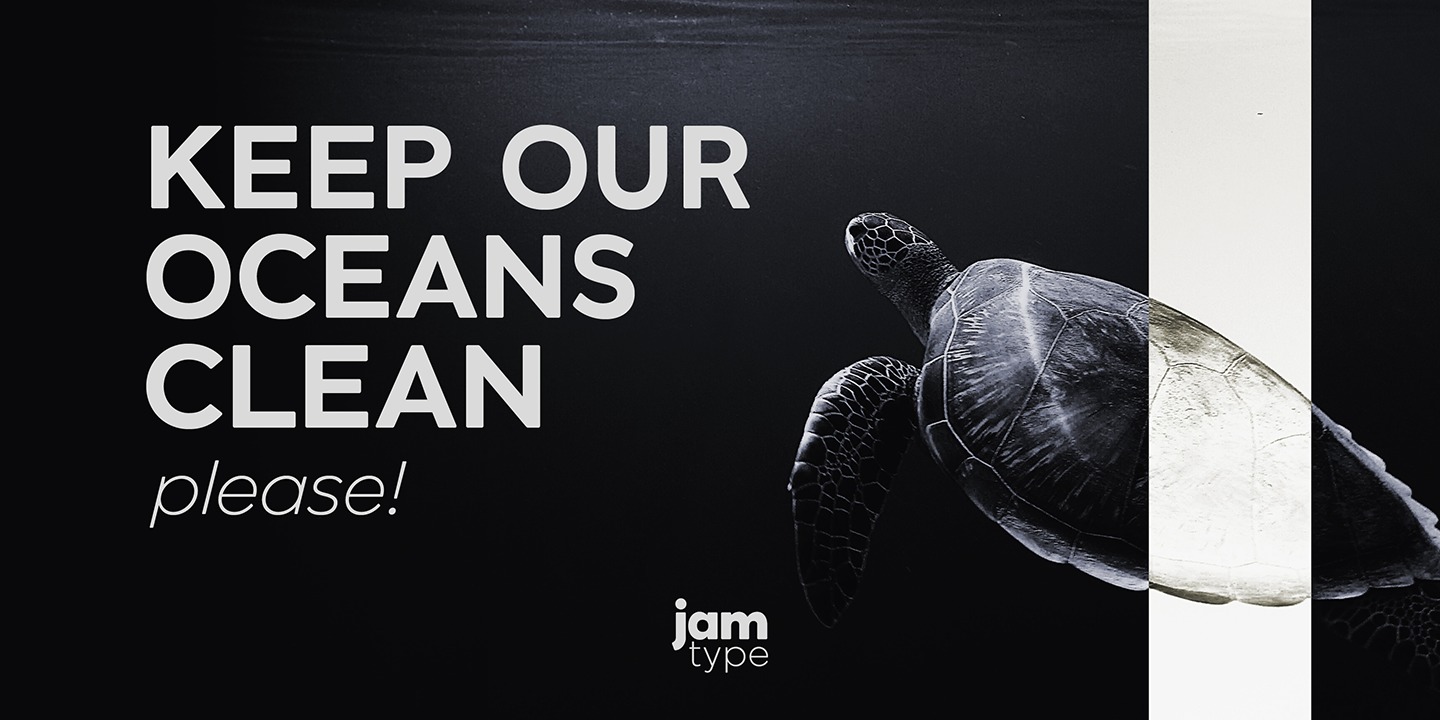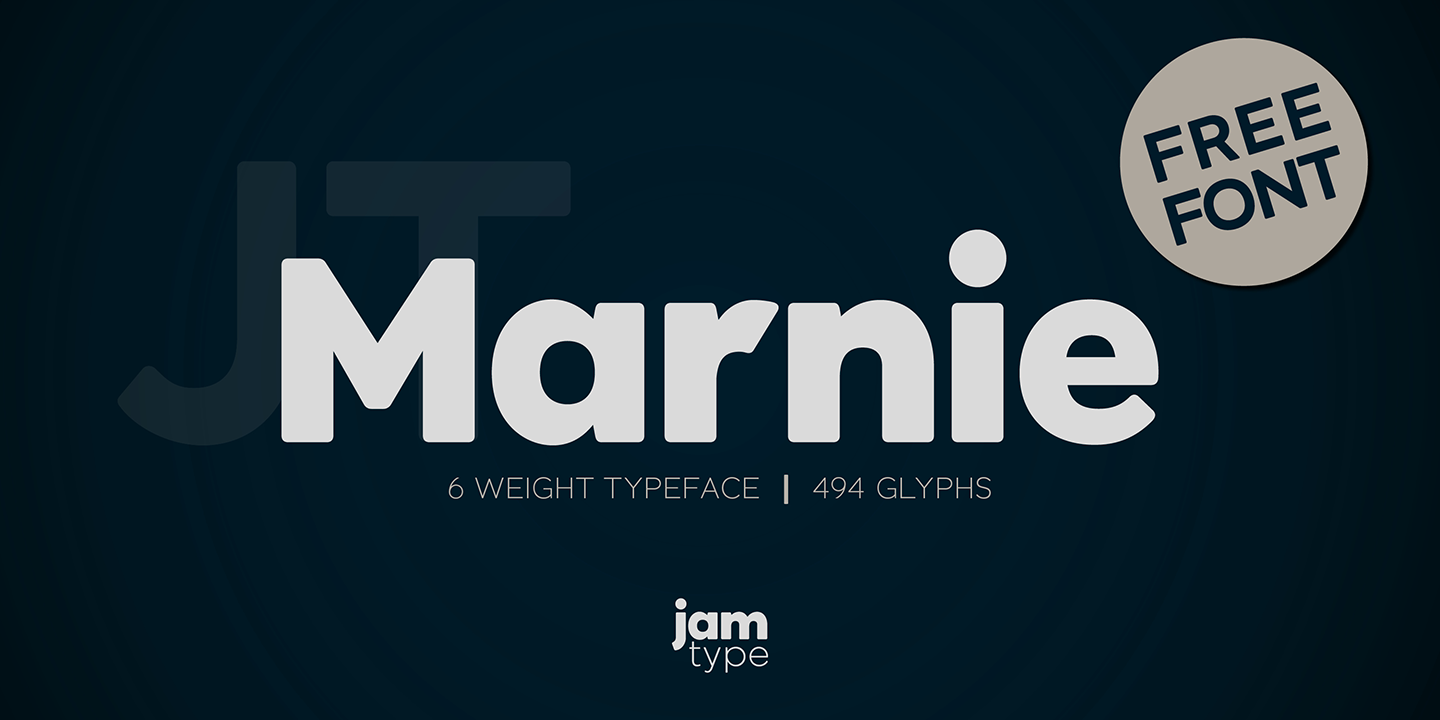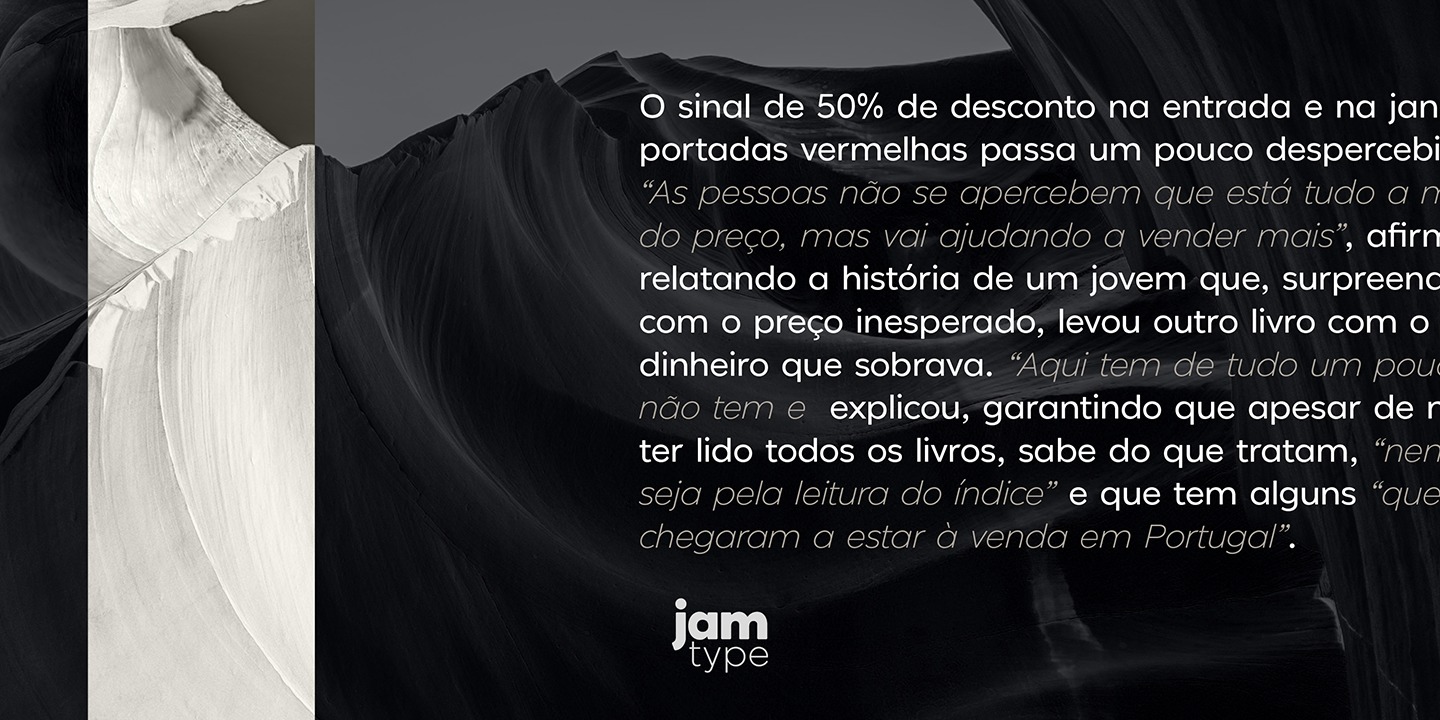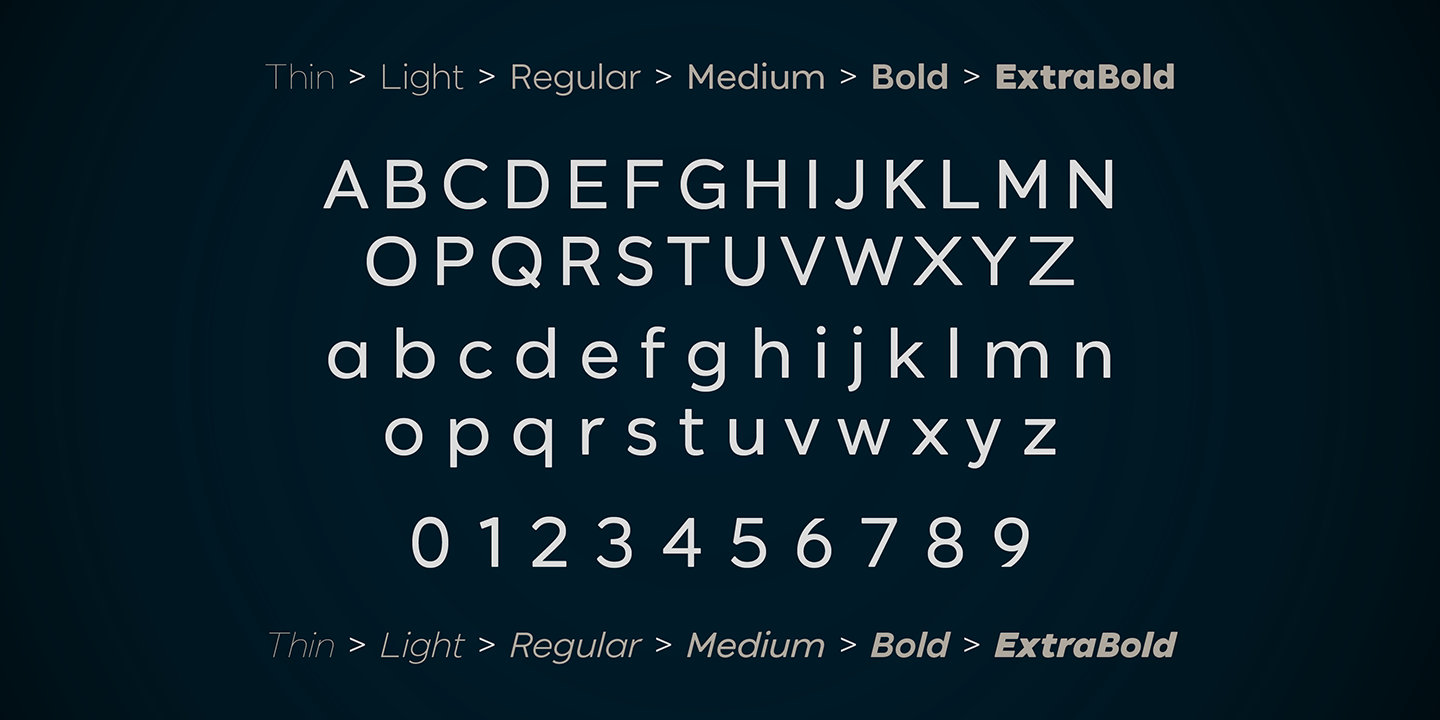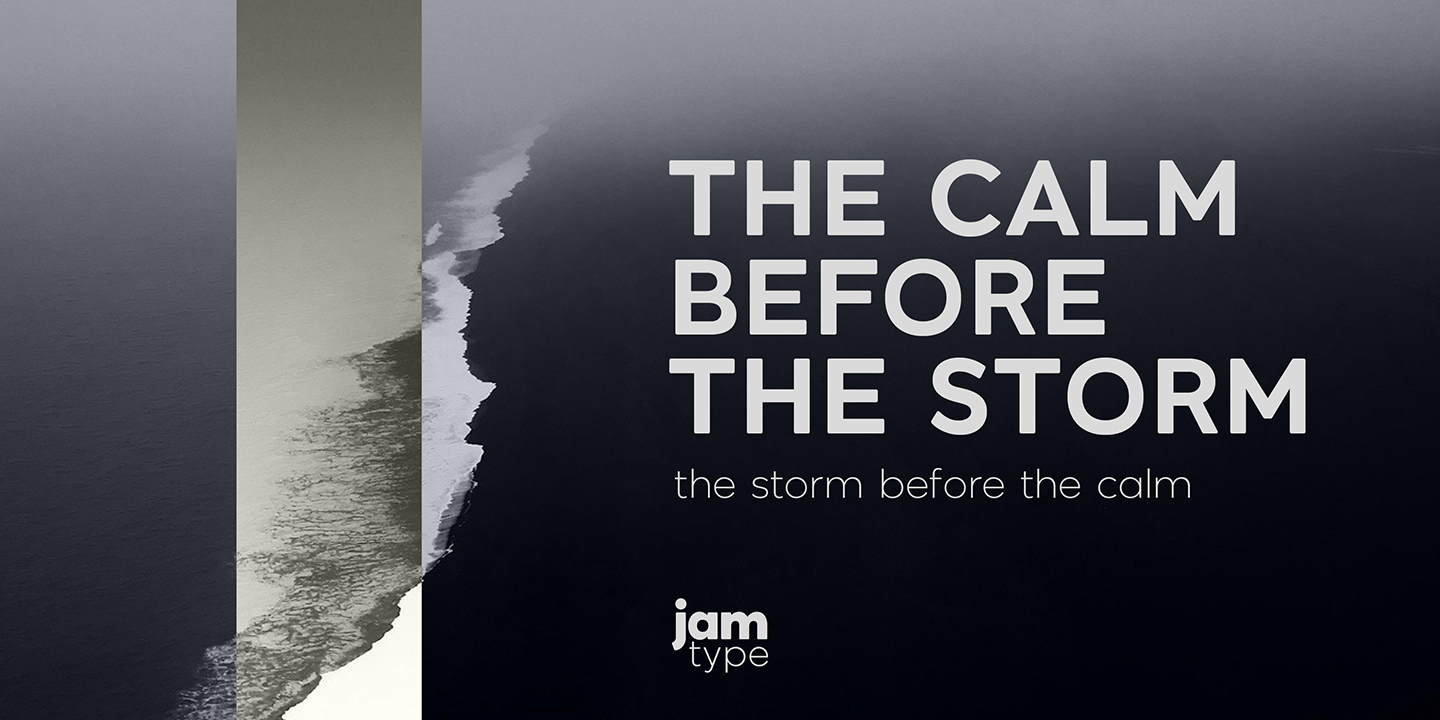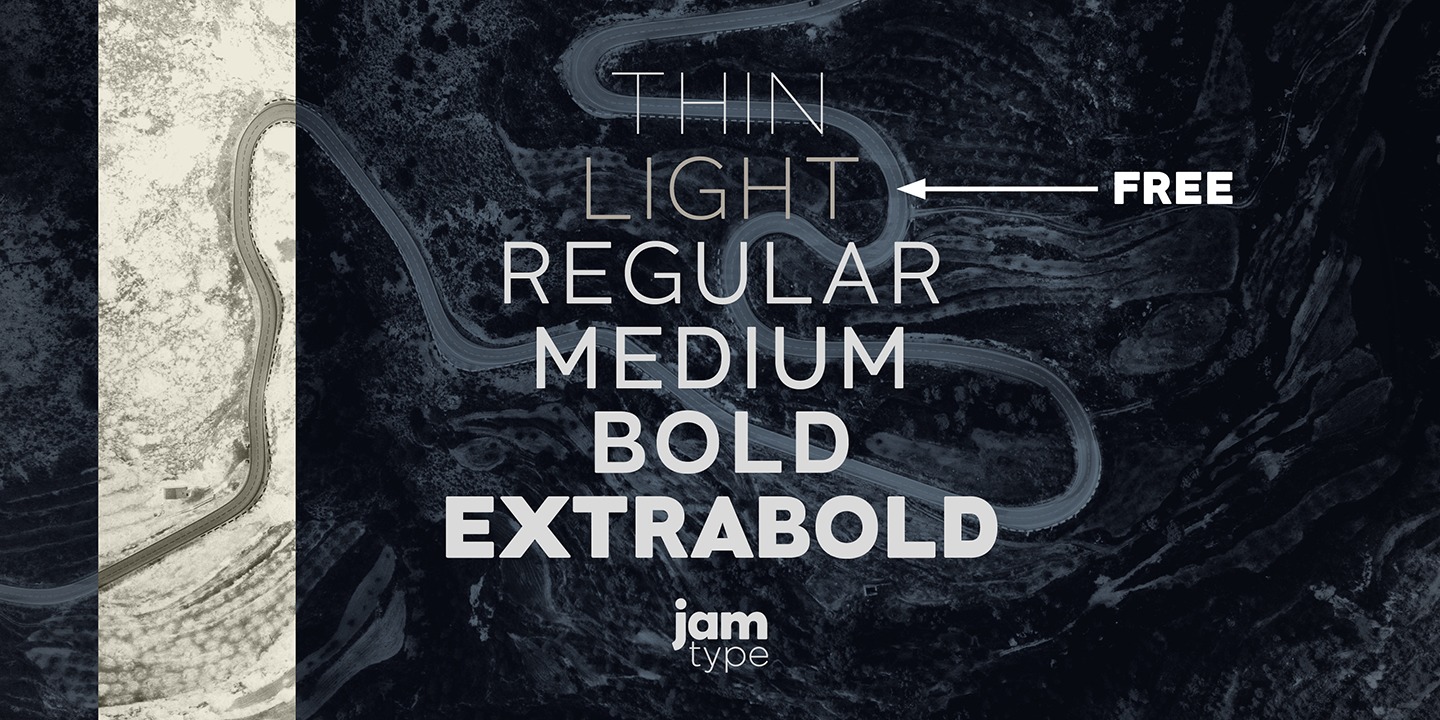
Thiết kế bị ảnh hưởng bởi các mặt sans serif theo phong cách hình học rất phổ biến trong những năm 1920 và 1930. Bộ font chữ JT Marnie rất phù hợp cho các tiêu đề và các khối văn bản nhỏ, đặc biệt là trong quảng cáo và bao bì.